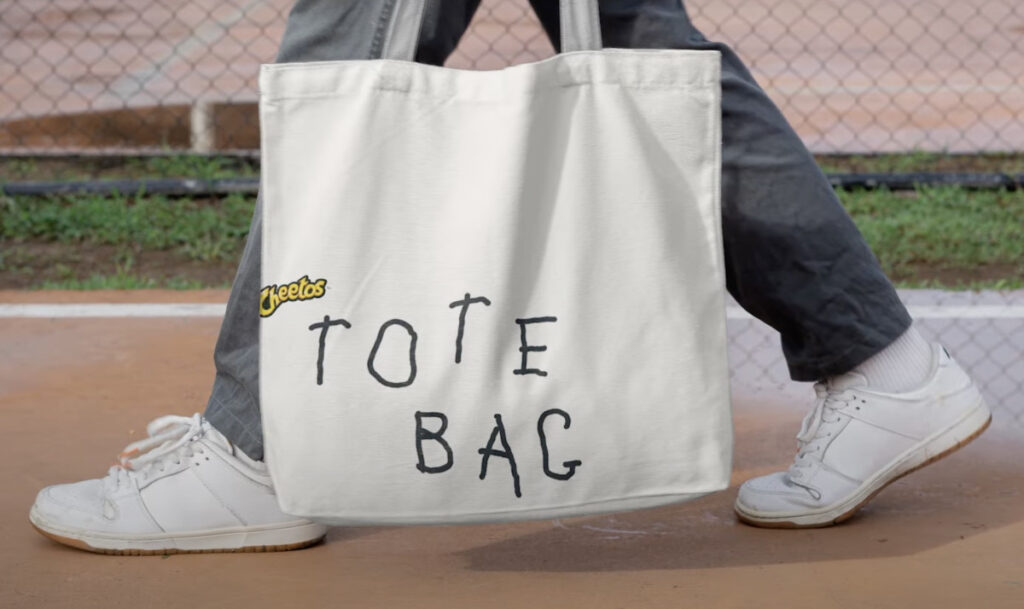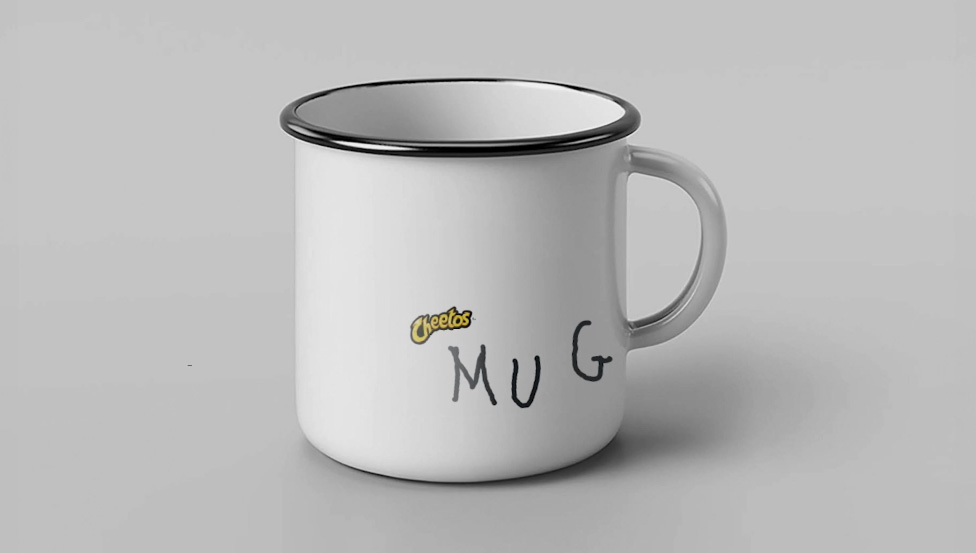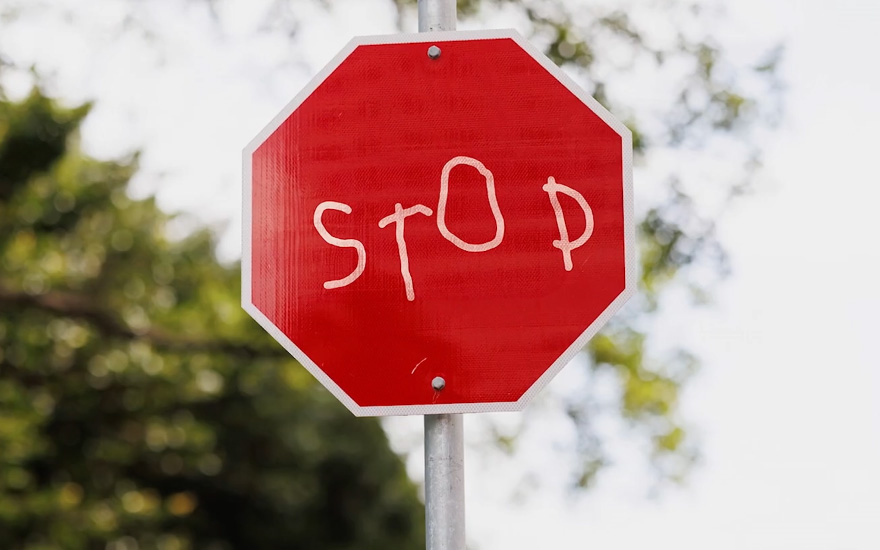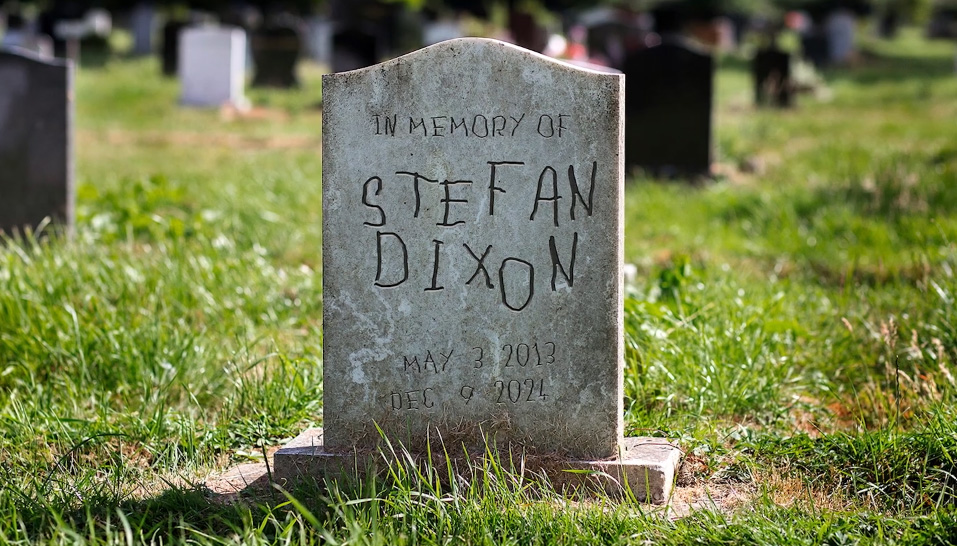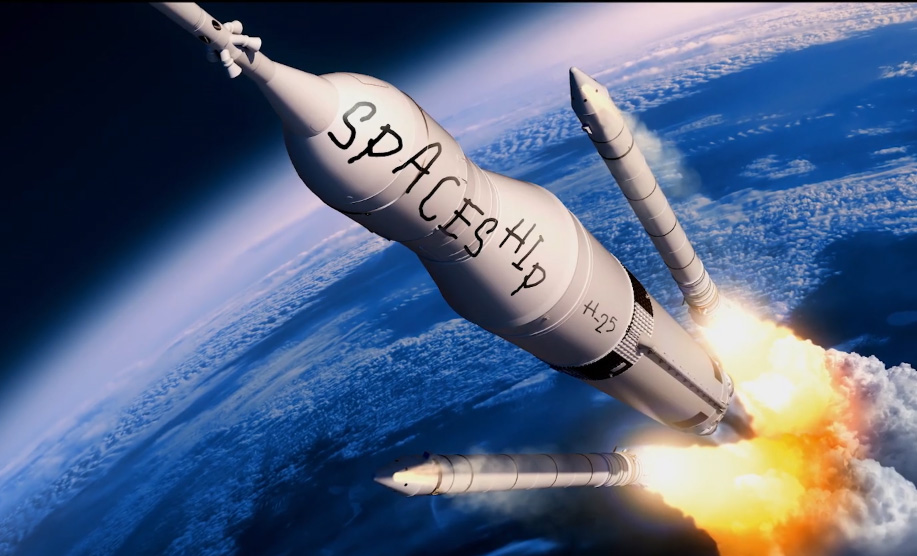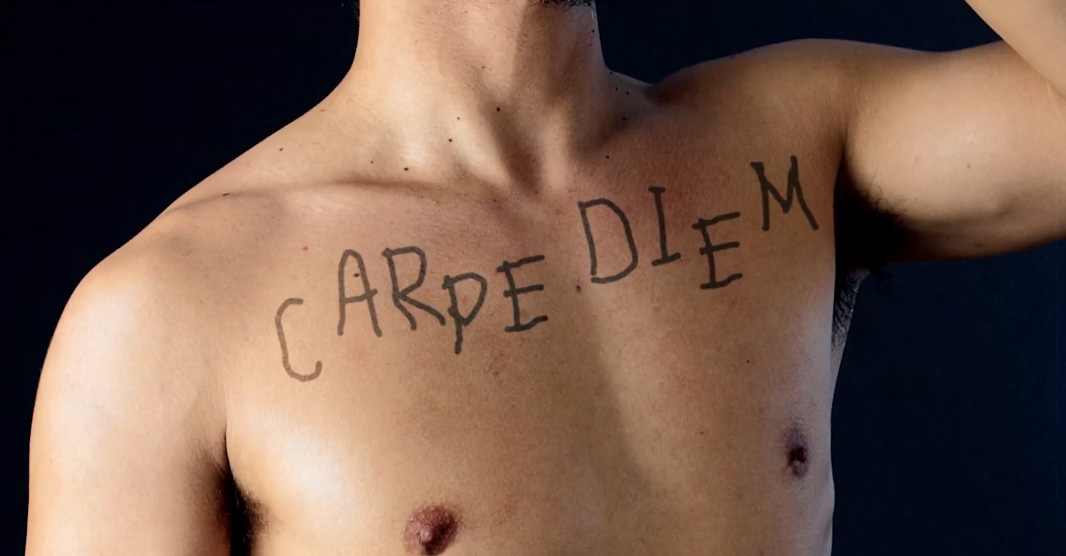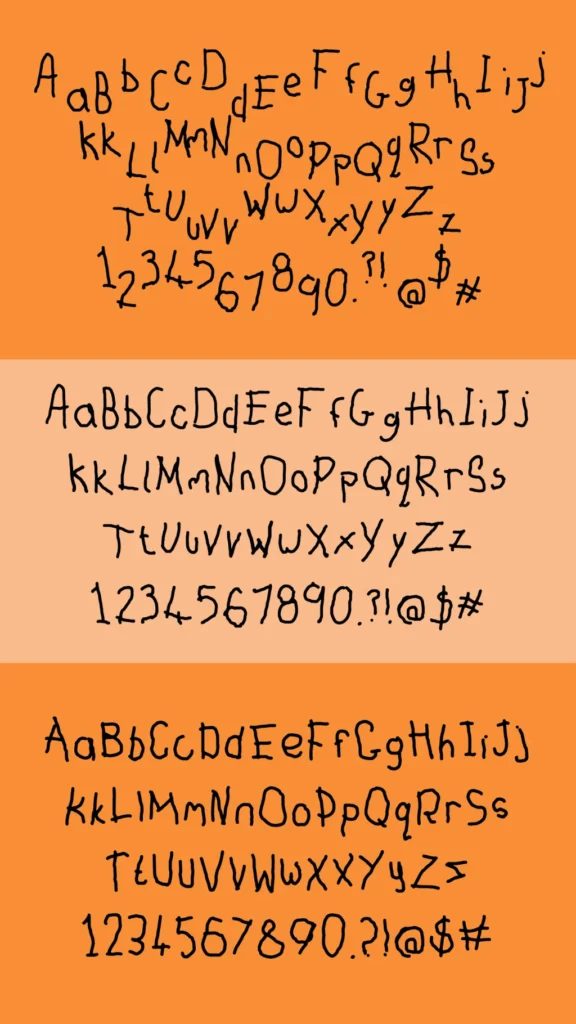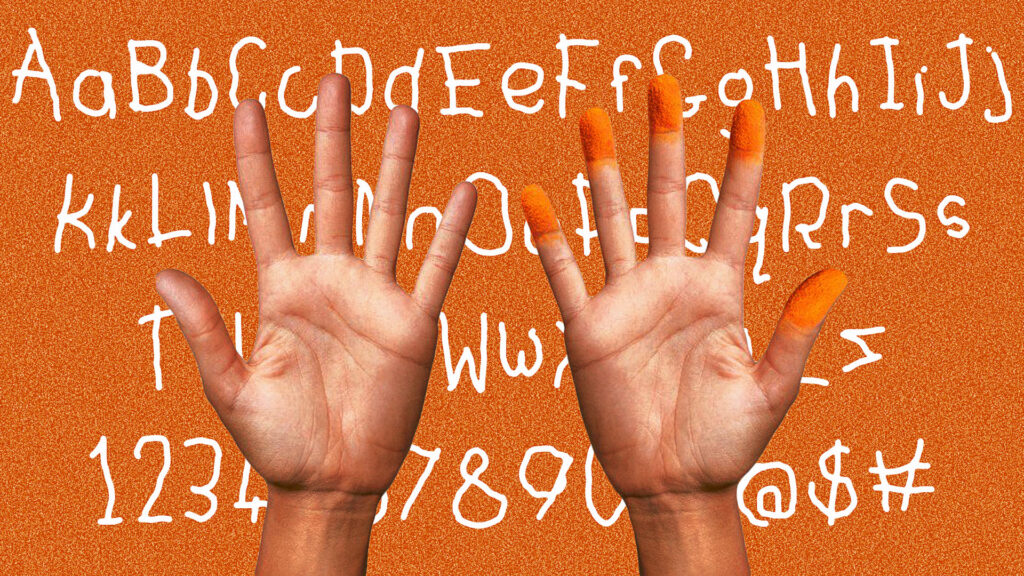
Cheetos разработали «худший шрифт в мире»
Бренд закусок представил шрифт «Other Hand»
Бренды часто превращают свои логотипы в шрифтовые алфавиты, которые фанаты могли использовать на разных платформах. Однако Cheetos применили другой подход, вдохновленный фирменной оранжевой пыльцой, которая осыпается при употреблении их продукта.
Вместо того чтобы разработать шрифт на основе своего узнаваемого логотипа, бренд закусок представил шрифт «Other Hand».
Шрифт доступен для загрузки или использования через расширение для браузера, а в рекламном видеоролике дизайнеры из рекламного агентства SG&P демонстрируют этот процесс, их пальцы окрашены в оранжевый цвет, и они рассказывают о том, что послужило источником вдохновения для его создания.